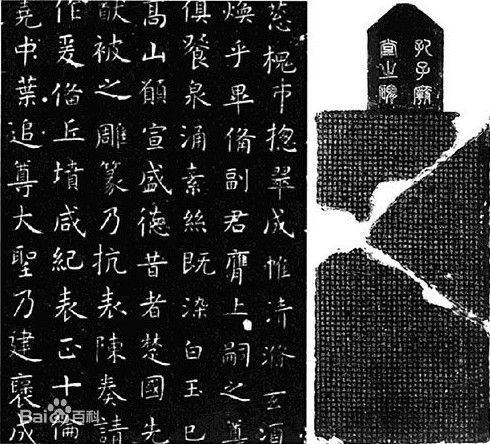
虞世南,初唐著名书法家、文学家、诗人、政治家。善书法,其书法刚柔并重,骨力遒劲,与欧阳询、褚遂良、薛稷合称“初唐四大家”。日本学界称欧阳询、褚遂良、虞世南为“初唐三大家”。其所编的《北堂书钞》被誉为唐代四大类书之一,是中国现存最早的类书之一。
虞世南喜书法,与王羲之七世孙智永和尚友善。智永精王羲之书法,虞世南在智永的精心传授下,妙得其体,圆融遒丽,外柔内刚,继承了二王(王羲之,王献之)书法传统。他与当时的欧阳询、褚遂良、薛稷合称唐初四大书法家,而虞世南又是四人中最优者。
虞世南是跟从王羲之的七世孙、隋朝书法家智永禅师学习书法的。他的字用笔圆润,外柔内刚,结构疏朗,气韵秀健。传说唐太宗学书就是以虞世南为师。
孔子庙堂碑为虞世南撰文并书写。原碑立于唐贞观初年。楷书35行,每行64字。碑额篆书阴文“孔子庙堂之碑”六字。碑文记载唐高祖五年,封孔子二十三世后裔孔德伦为褒圣侯,及修缮孔庙之事。为虞世南六十九岁时所书。
孔子庙堂碑虞世南
唐太宗称他德行、忠直、博学、文词、书翰为五绝(世南一人,有出世之才,遂兼五绝。一曰忠谠,二曰友悌,三曰博文,四曰词藻,五曰书翰。)